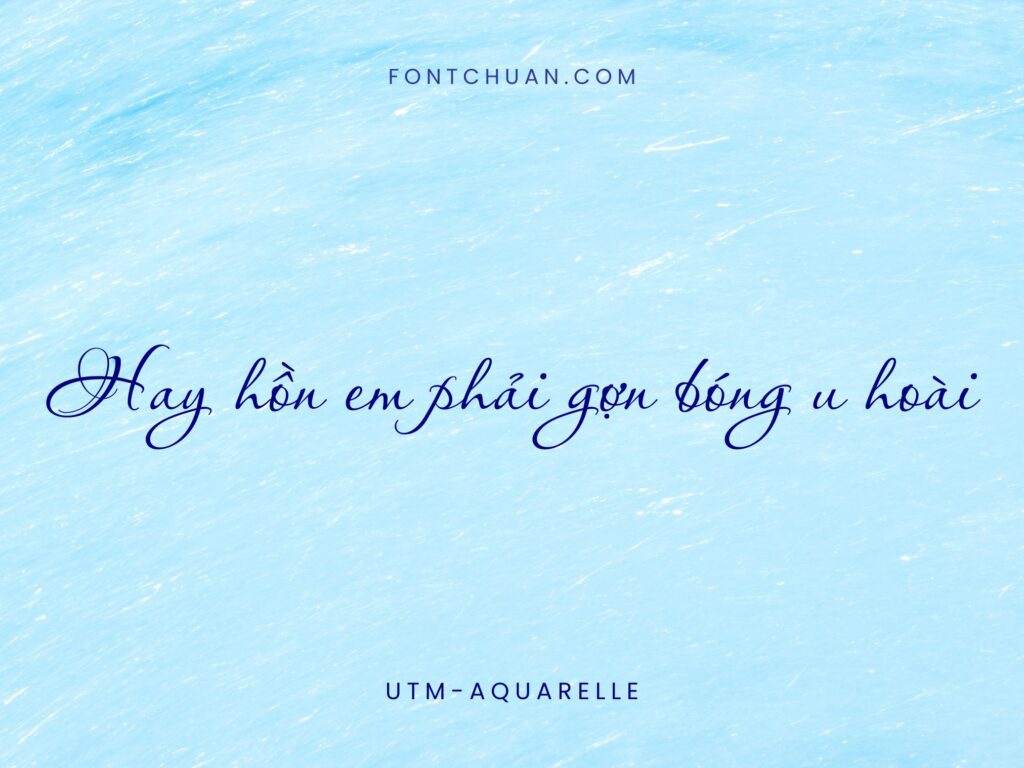
Font UTM Aquarelle Việt Hóa
UTM Aquarelle là phiên bản Việt hóa của một Font Script mang phong cách Font Handwritten mềm mại, tự nhiên và thanh lịch. Font này được thiết kế theo kiểu chữ viết tay nhẹ nhàng, tạo cảm giác uyển chuyển và tinh tế trong từng đường nét. Phiên bản Việt hóa do Đinh Kiên thực hiện, hỗ trợ đầy đủ tiếng Việt cùng hơn 100 ngôn ngữ khác. Thành viên của Font Chuẩn đã sưu tầm và chọn lọc font này nhằm đáp ứng nhu cầu đa dạng của bạn đọc và ứng dụng thực tế vào các dự án thiết kế.
UTM Aquarelle có cấu trúc chữ với các nét uốn lượn tự nhiên, tạo cảm giác gần gũi và thân thiện. Font này phù hợp cho các ứng dụng như thiết kế thiệp mời, logo, tiêu đề và các ấn phẩm in ấn yêu cầu sự tinh tế và cá nhân hóa. Các ngành nghề như quảng cáo, thiệp cưới, giáo dục và ẩm thực có thể tận dụng UTM Aquarelle để tạo điểm nhấn độc đáo trong thiết kế.